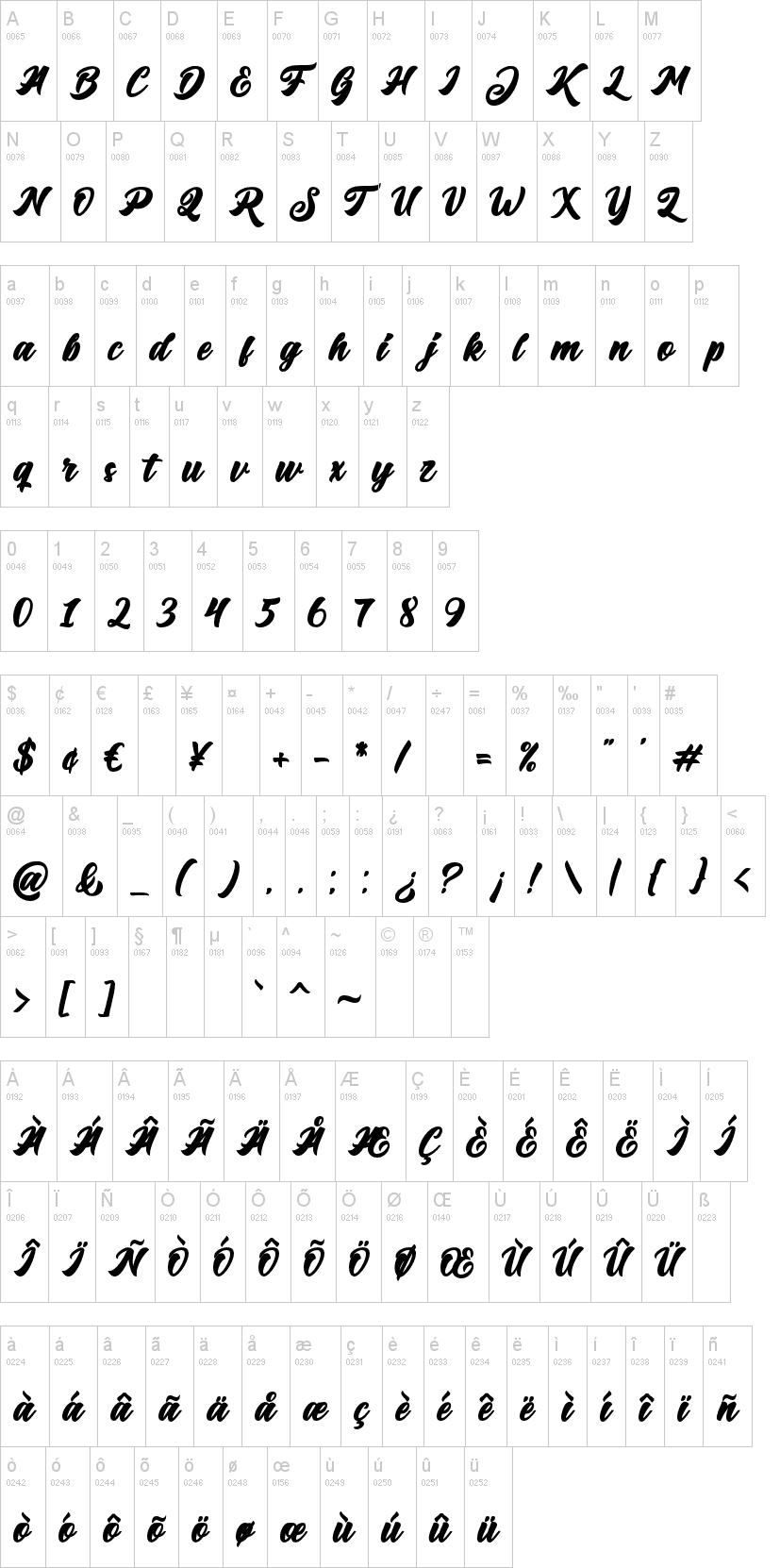
Big Blue
Big Blue 是一款由美国设计师 Matthew Welch 创作的免费字体,它是一种复古风格的显示字体,外观优美,特点是圆润的字形,粗细比例合理,可以用于报纸、杂志、海报等多种印刷品的设计。它的字符设计简洁而清晰,可以使文本内容更加突出,并且在不同尺寸的文字中保持一致的风格,使用者可以放心使用。
Big Blue是一款非常不错的手写艺术字体,具有很好的视觉感,适合于文化类的宣传设计、商业类品牌的广告和产品包装设计以及个性化文字排版等较多场景。
Big Blue字符映射图